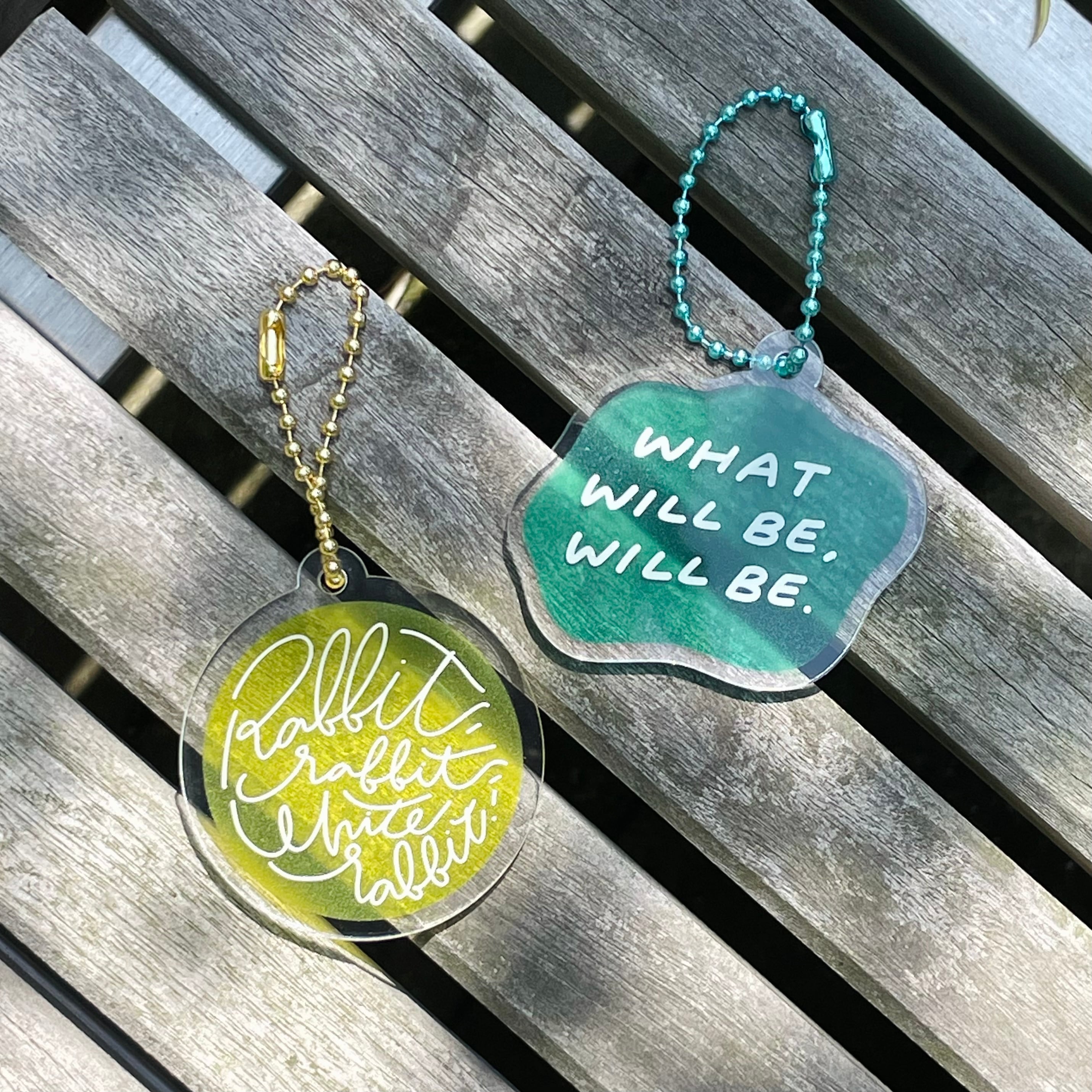
アクリルキーホルダー/Rabbit,Rabbit,White Rabbit!
ポジティブになれる言葉のキーホルダー作りました!
Rabbit,Rabbit,White Rabbit!
月の初めの日に唱えると、その月はいいことがあるかも?というおまじない
よーく見ると、ウサギの耳みたいに見えるところがあります!!
形も月みたい??
黄色い背景は透けていて涼しげにしました。